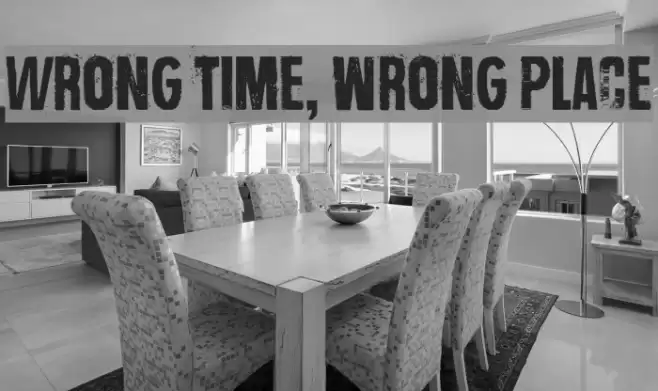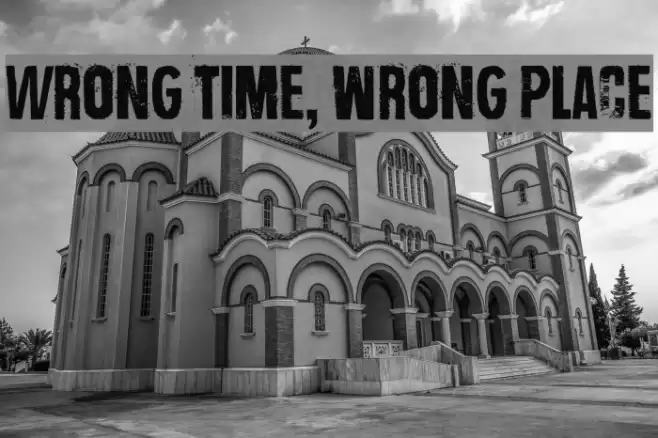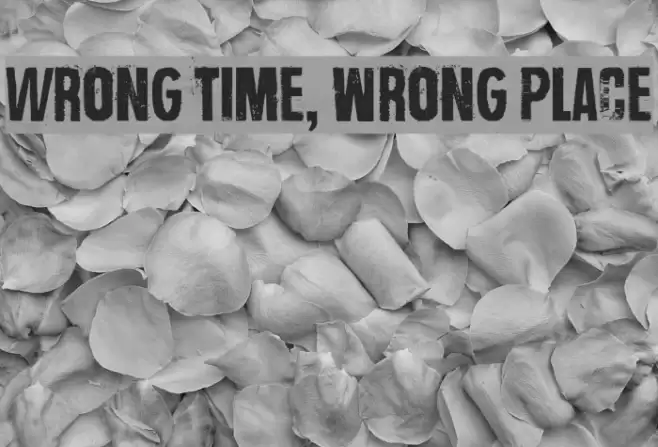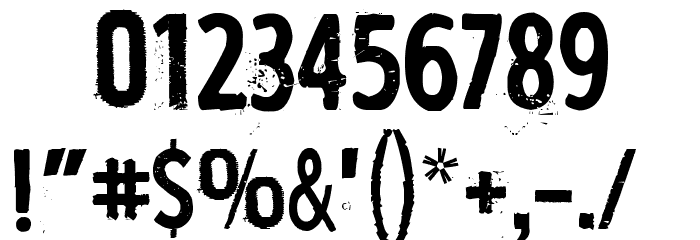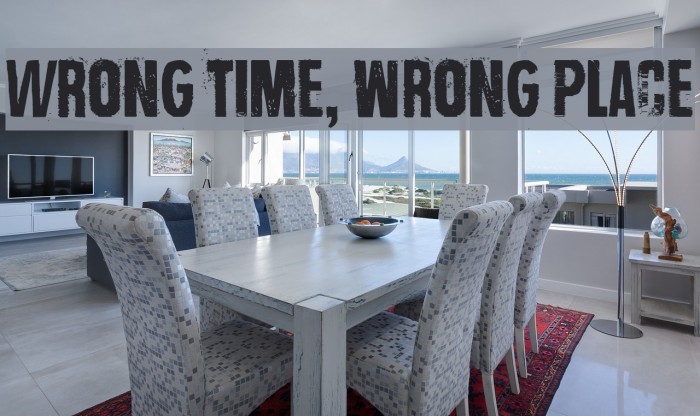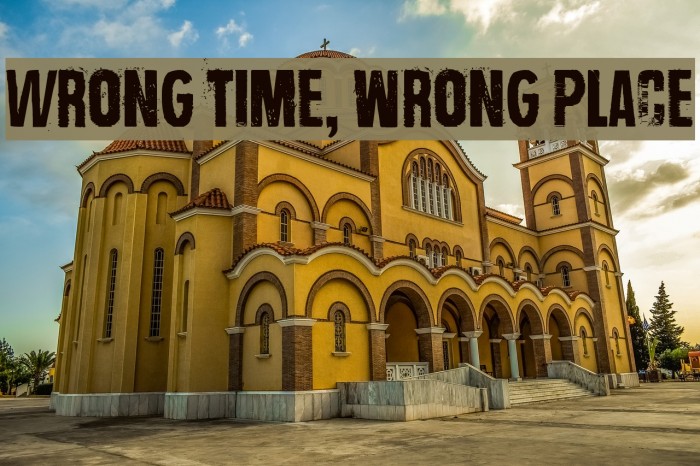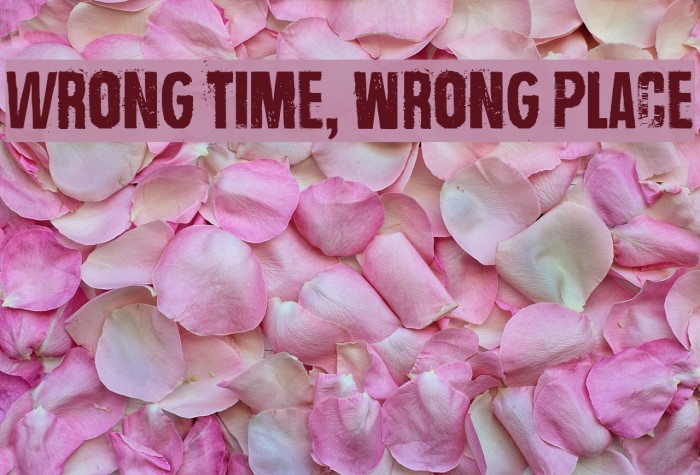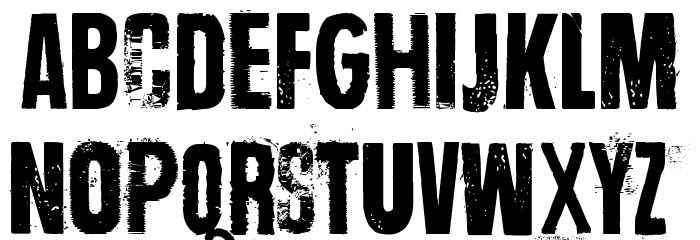
Wrong time, wrong place Font
CategoriasFancy
NegritoYes
ItálicoNo
LarguraNormal
Espaçamento de caracteresMonospaced
ContrasteMedium
Estilo geralVintage, Grunge
Caso de usoHeadlines, Logos, Posters
Projetos propostosIdeal for posters, album covers, branding for edgy or retro-themed products, and any design needing a bold, textured look.